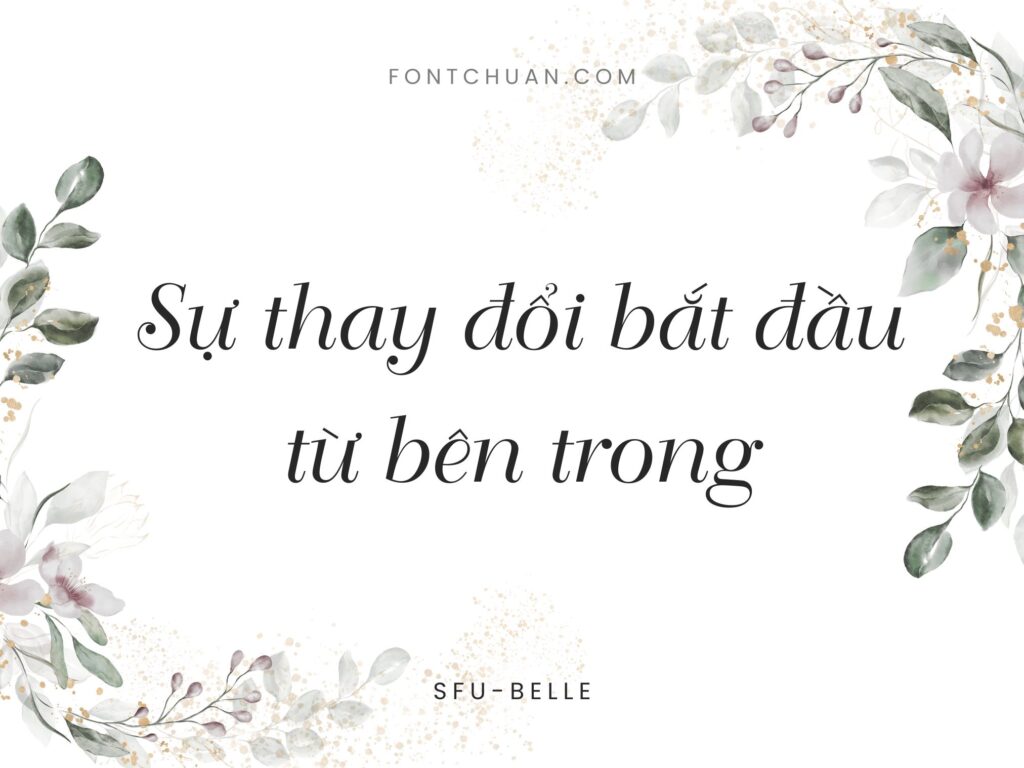
Font Belle là một kiểu chữ trang trí độc đáo, mang phong cách fancy và various, được thiết kế bởi Nopianti. Với các đường nét mềm mại và tinh tế, Belle tạo nên sự thanh lịch và quyến rũ, phù hợp cho nhiều mục đích thiết kế khác nhau như thiệp mời, logo, tiêu đề và các dự án nghệ thuật. Font này hỗ trợ đầy đủ tiếng Việt, giúp người dùng dễ dàng ứng dụng trong các dự án đa ngôn ngữ
Về đặc điểm thiết kế, Belle có cấu trúc chữ cái độc đáo, với sự kết hợp giữa các nét cong mềm mại và các chi tiết trang trí tinh tế, tạo cảm giác sang trọng và thu hút. Kiểu chữ này rất phù hợp để sử dụng trong các thiết kế như thiệp mời, logo, tiêu đề và các ấn phẩm nghệ thuật